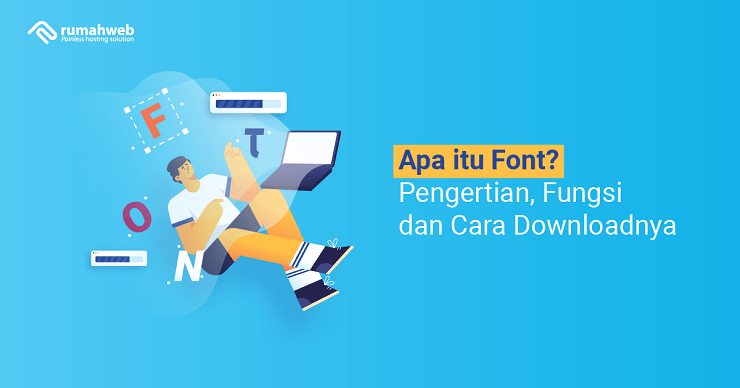
Font adalah gaya tulisan yang biasa digunakan saat mengetik di PC maupun HP. Tahukah Anda bahwa sebelum tersedia di perangkat digital, font adalah hasil dari ukiran tangan manusia? Faktanya, font sudah muncul sejak berabad-abad lalu.
Kemunculan font diperkirakan terjadi ketika teknik percetakan pertama kali ditemukan di daerah Asia Timur berabad-abad yang lalu. Ketika itu, orang-orang di China menggunakan cetakan balok kayu pada kain dan kertas.
Seiring perkembangan zaman dan beralihnya kebiasaan membaca dari kertas ke layar, pembuatan font tidak lagi dilakukan secara manual, tetapi dilakukan secara digital. Kini font menjadi bagian penting dalam industri teknologi. Keberadaannya bahkan dapat memengaruhi minat individu yang menjadi target dalam pemasaran.
Pengertian Font
Seperti yang sudah disinggung sebelumnya, font adalah style, atau gaya tulisan, yang dapat digunakan di peranti lunak. Pada beberapa software, seperti Microsoft Word, gaya font ini dapat dibagi menjadi tiga: bold, italic, dan underline.
Bold bisa digunakan jika ingin tulisan Anda menjadi tebal, italic jika ingin tulisan menjadi miring, dan underline jika Anda ingin menggarisbawahi tulisan.
Namun, font juga bisa diartikan sebagai jenis huruf. Beberapa jenis font adalah Times New Roman, Calibri, Arial, Cambria, Comic Sans, dan masih banyak lagi lainnya. Berbagai font ini ada yang sudah tersedia di berbagai software, namun ada juga yang harus diunduh secara manual.
Fungsi dari Icon Font
Ketika Anda membuka Microsoft Word atau software lainnya, Anda akan menemukan sejumlah icon font. Fungsi dari icon font ini sangat banyak, di antaranya untuk mengubah tipe huruf, mengganti warna teks, mengubah ukuran teks, menebalkan tulisan, memiringkan tulisan, memberi garis bawah, mengubah huruf menjadi kapital atau kecil, dan memberi efek tulisan.
1. Font Style
Umumnya, font style pada software populer terdiri dari 3 jenis; bold (B), italic (I), dan underline (U). Seperti yang sudah dijelaskan di atas, fungsi bold font adalah untuk menebalkan huruf. Biasanya icon ini digunakan untuk menandai informasi penting dari suatu teks.
Kemudian, italic font adalah jenis font style yang digunakan untuk memiringkan huruf, dan biasanya digunakan untuk menulis istilah asing.
Underline font adalah font style terakhir yang dapat digunakan untuk memberi garis bawah suatu tulisan. Hampir sama seperti bold font, fungsi underline font adalah untuk menandai suatu informasi penting.
2. Font Size
Icon penting lainnya dari font adalah ukuran, atau font size. Icon ini dapat ditemukan pada tampilan home Microsoft Word, yang berfungsi untuk mengatur ukuran sebuah teks.
Biasanya, besar ukuran yang sudah tersedia dimulai dari 8, 9, 10, 11, 12, 14, 16, 18, 20, 22, 24, 26, 28, 36, 48, sampai 72. Namun, Anda juga bisa mengatur secara custom dengan memasukkan angkanya secara langsung.
3. Font Color
Selain style dan size, Anda juga bisa mengatur warna dari font. Color font adalah icon yang ada pada bagian home Microsoft Word dan berfungsi untuk mengatur warna teks.
Selain font color, ada juga text highlight color untuk menstabilo atau menandai tulisan, serta text effect dan typography untuk memberi efek pada tulisan seperti bayangan, refleksi, atau kilauan.